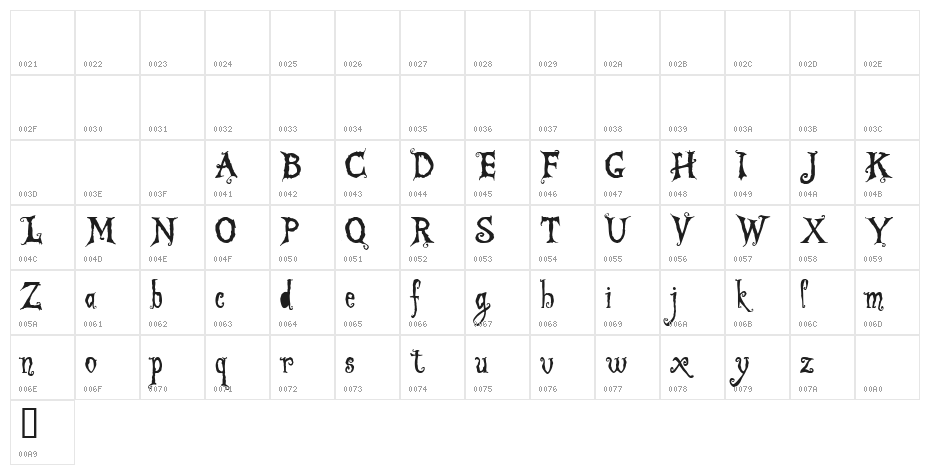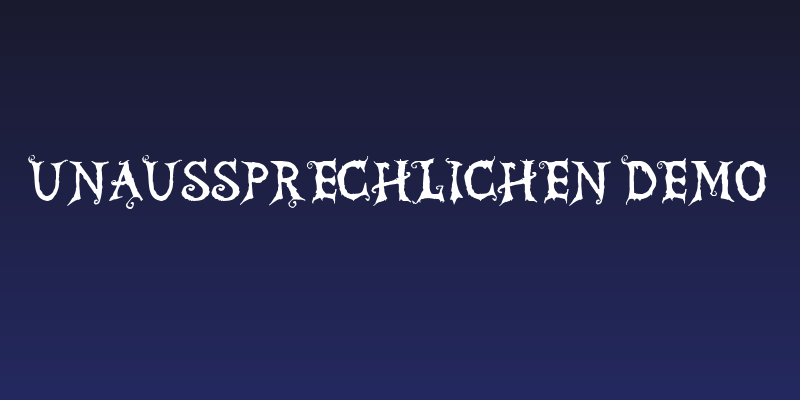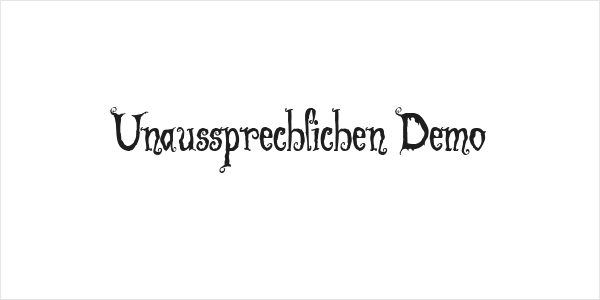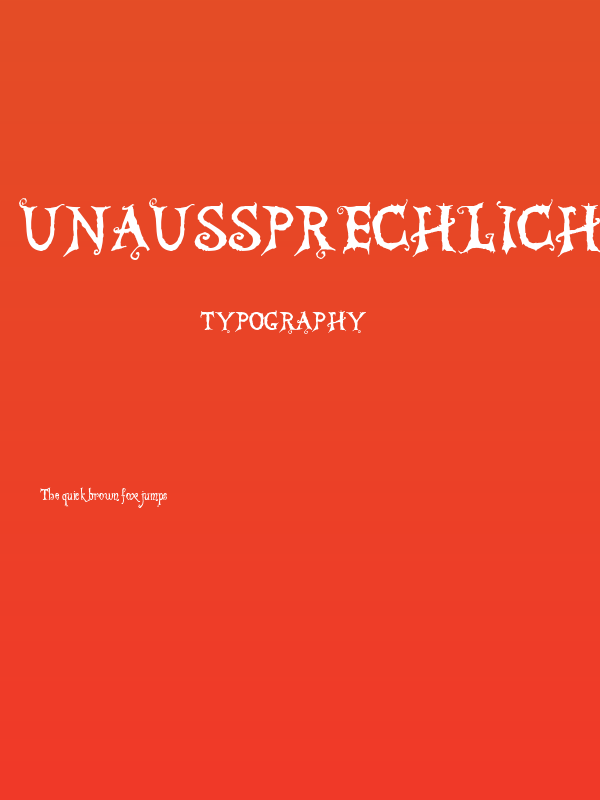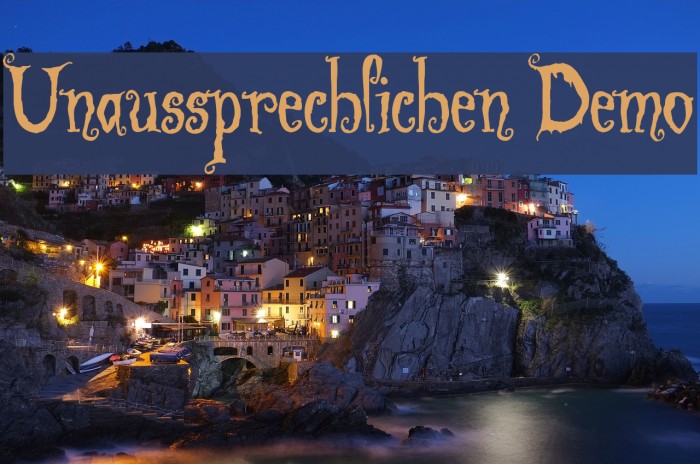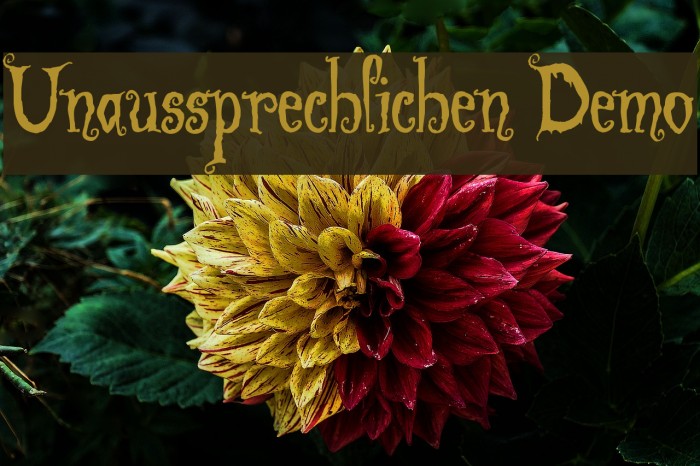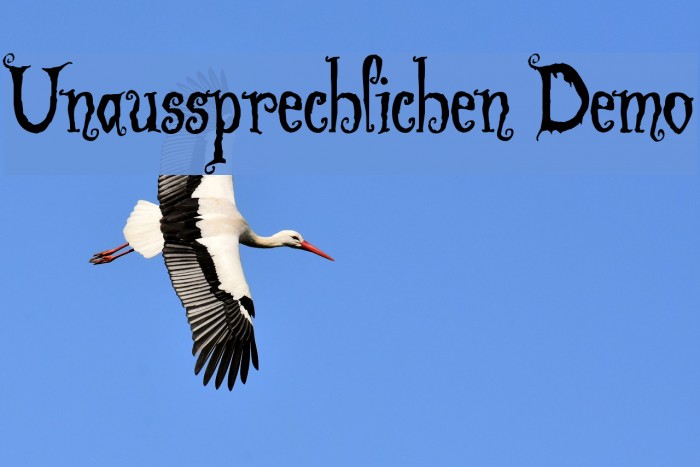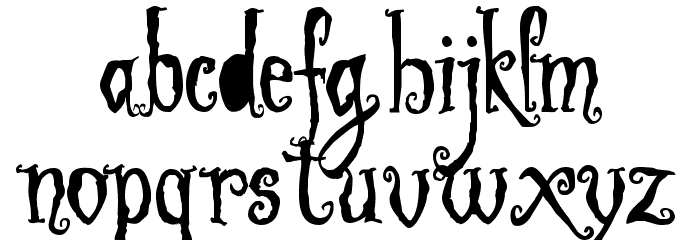
Unaussprechlichen Demo Font
✎ Formal
| Categorie | Formal |
| Progetti proposti | Ideal for fantasy book covers, Halloween-themed designs, theatrical posters, and artistic invitations. |